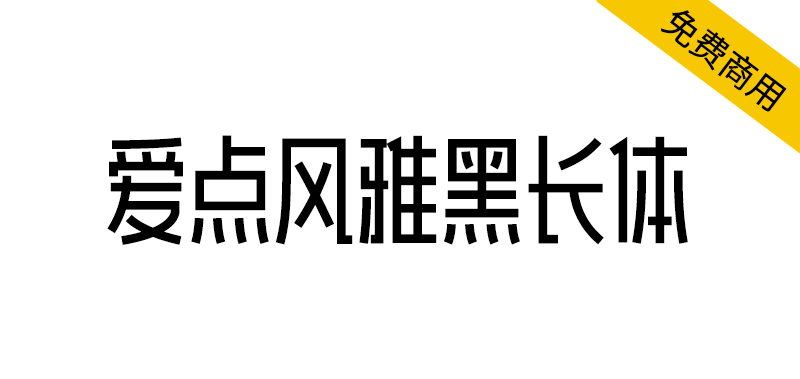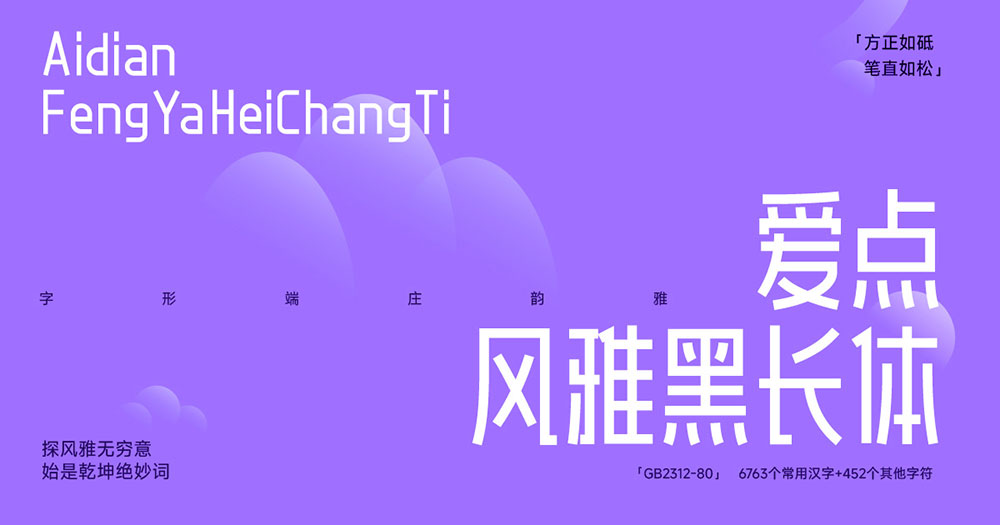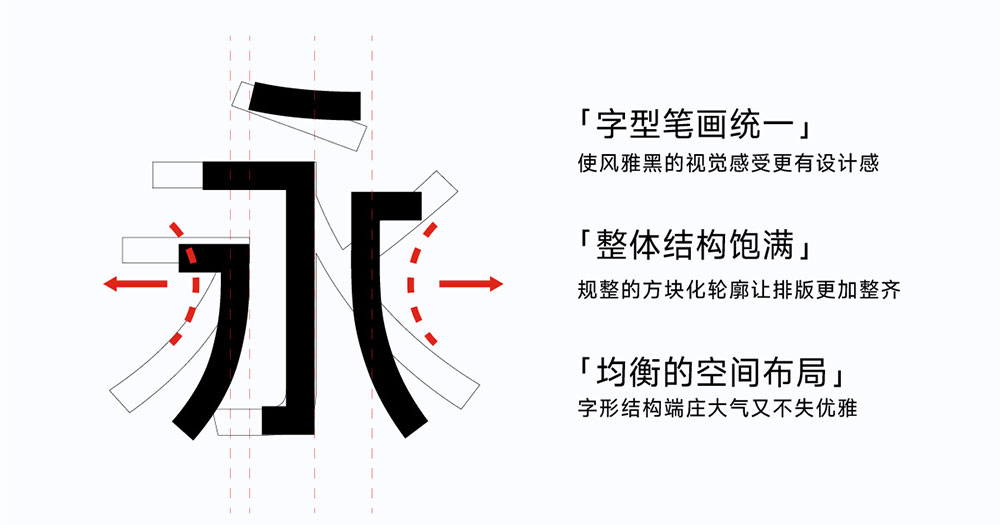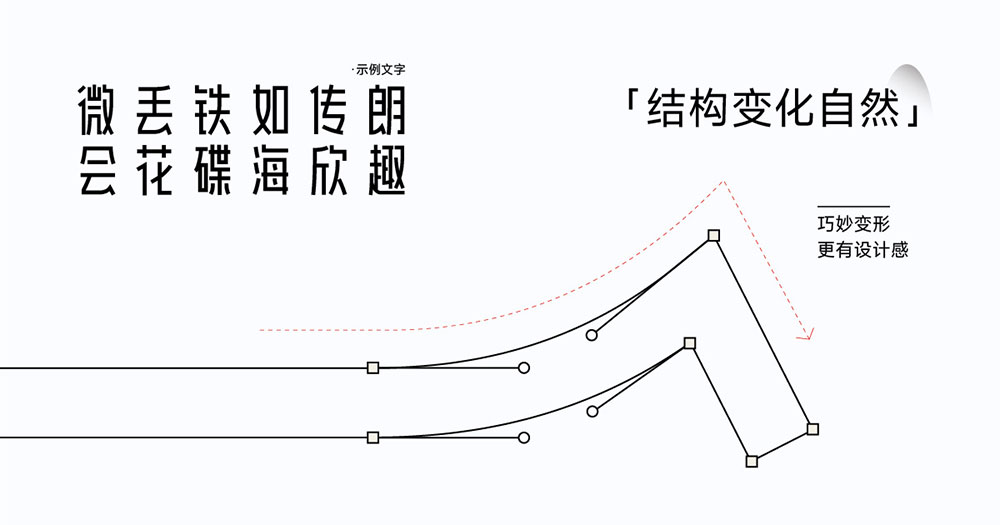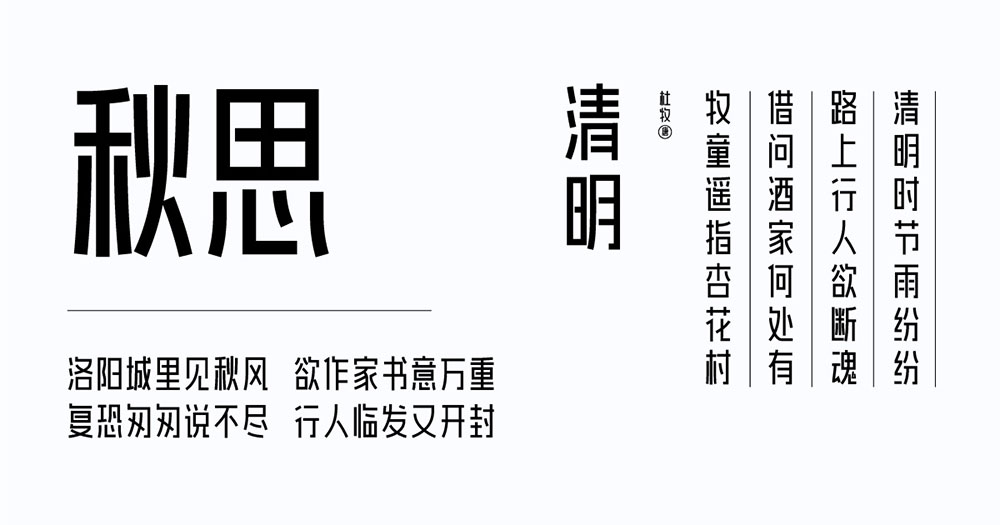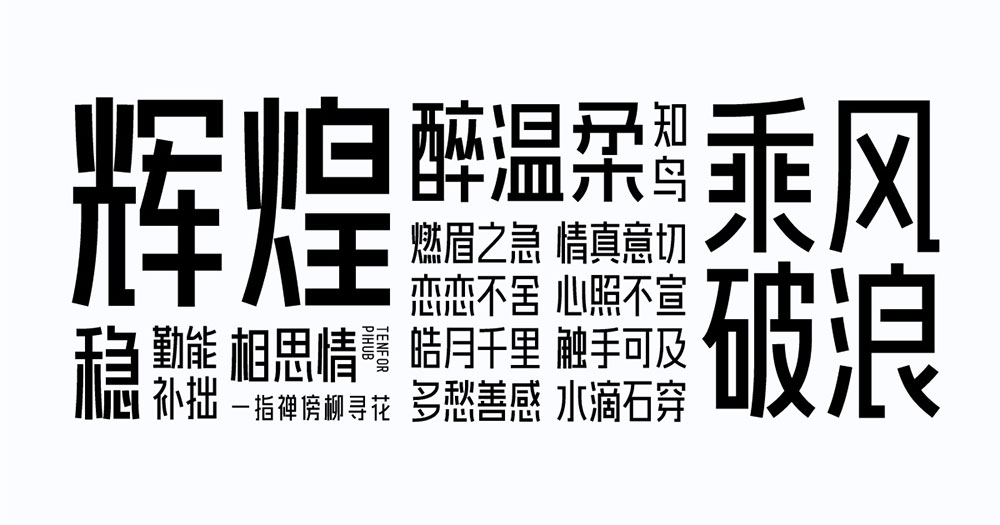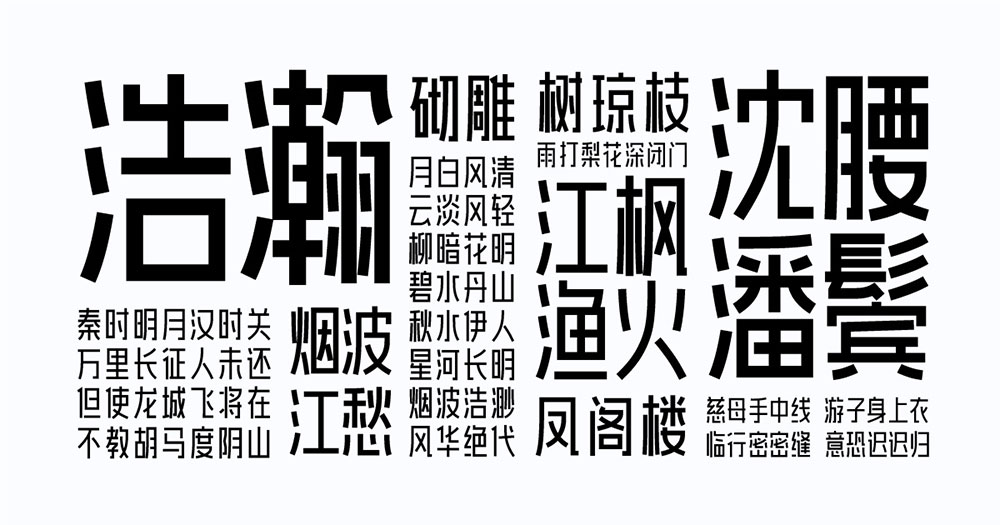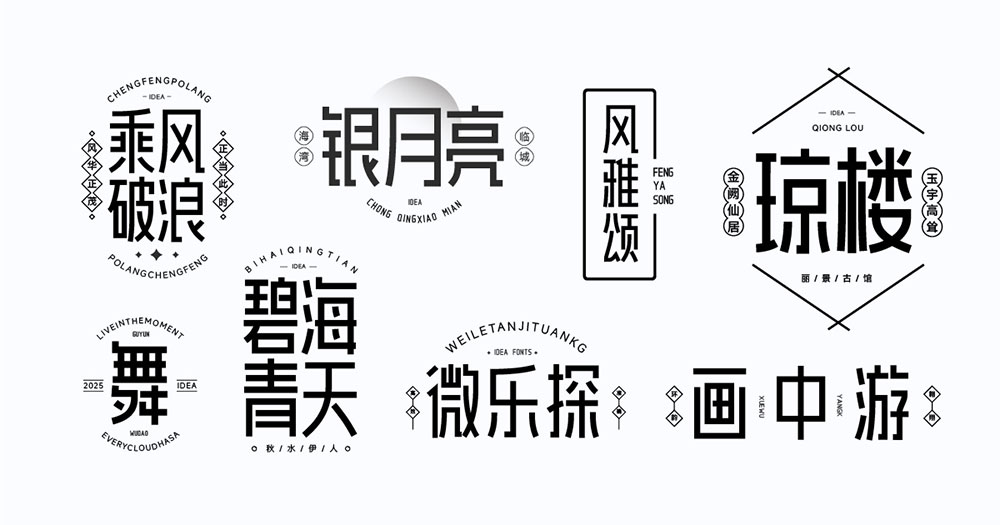
【爱点风雅黑长体】一款高挑时尚的免费黑体字体
还在为商业设计找不到免费又高级的字体发愁?这款高挑时尚的黑长体彻底打破困局——爱点风雅黑长体正式开放永久免费商用!包含6763个常用汉字,笔触端庄挺拔如松,完美适配广告设计与UI界面。无需担心版权风险,个人与企业均可直接用于电商、自媒体等场景。立即解锁这款兼具美感与实用性的字体,让你的设计瞬间提升专业度!
【爱点风雅黑长体】一款高挑时尚的免费黑体字体
爱点风雅黑长体是广州爱点视觉文化有限公司(爱点字库)基于“爱点风雅黑”开发的商用免费字体,个人及企业可永久免费使用。该字体高挑时尚、端庄韵雅、方正如砥、笔直如松,可免费用于各类广告、UI设计用途。符合GB2312-80中国国家标准汉字编码字符集标准,包含有6763个常用汉字及452个其他字符。